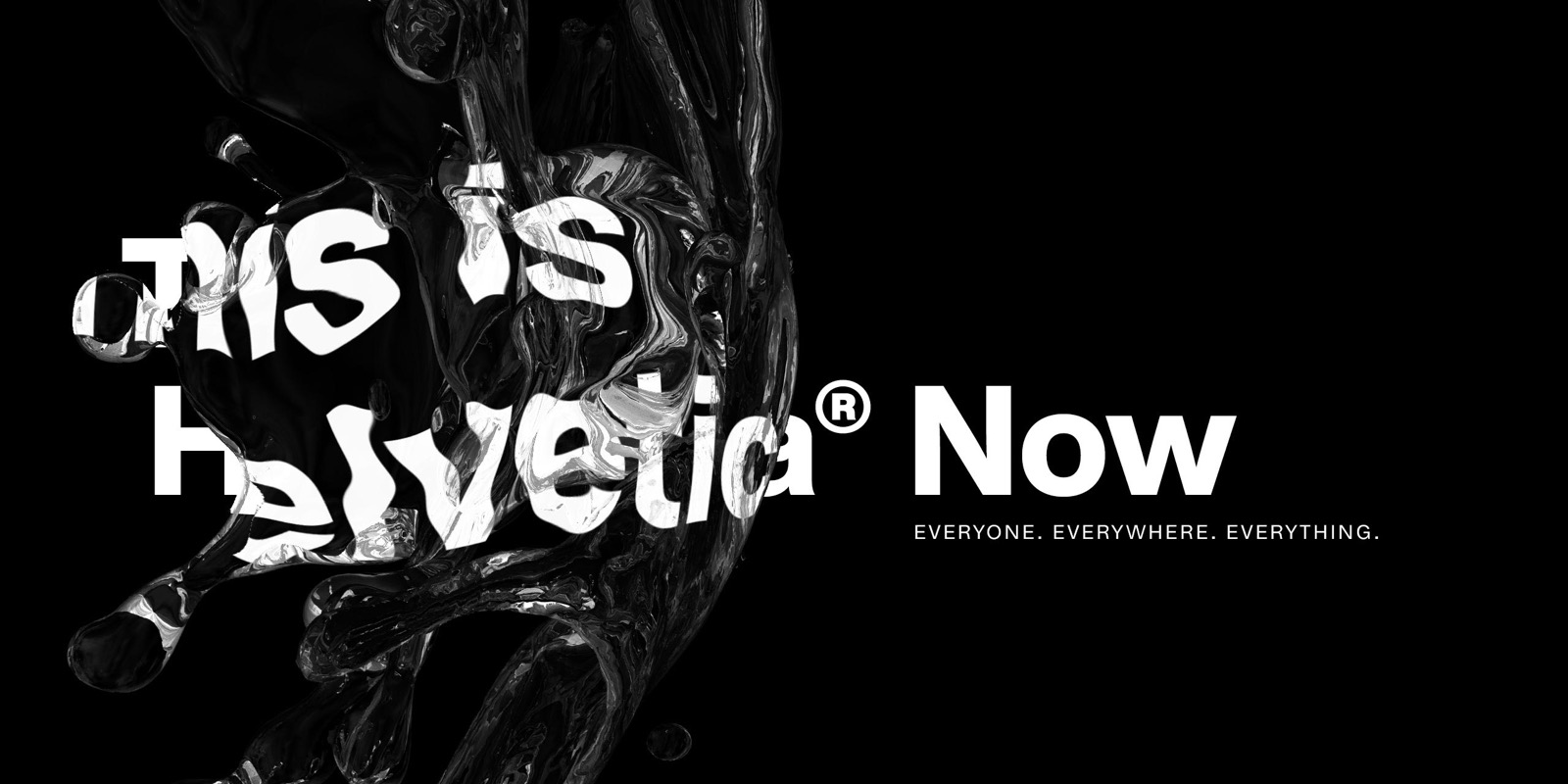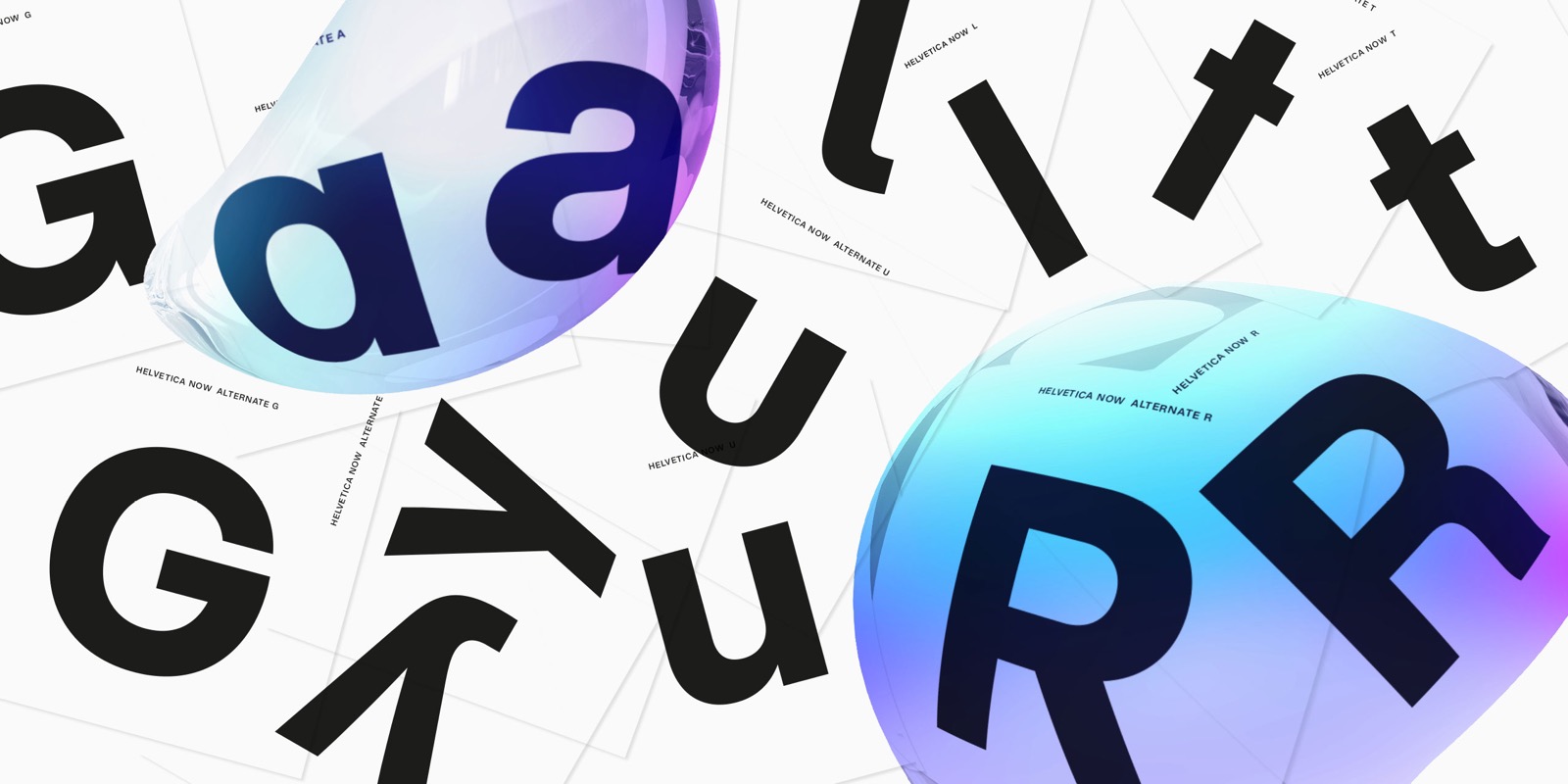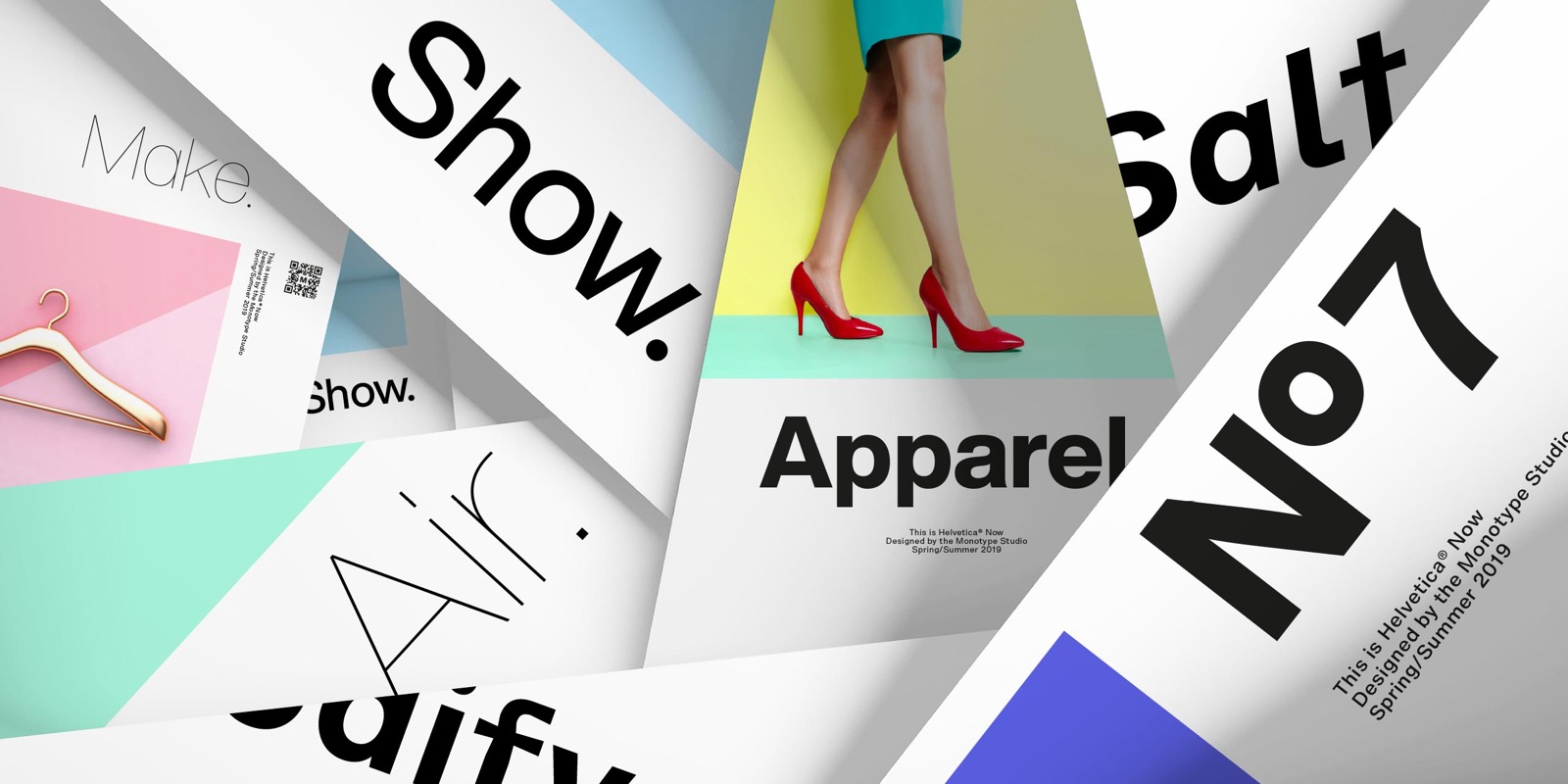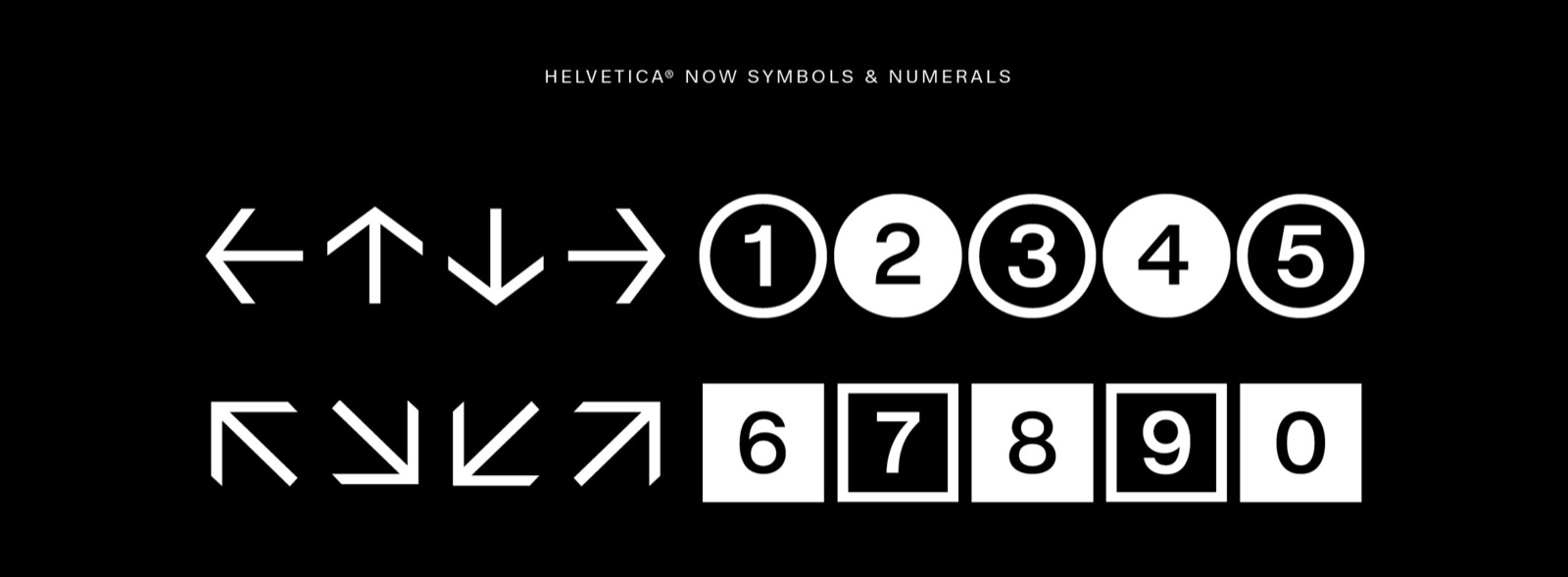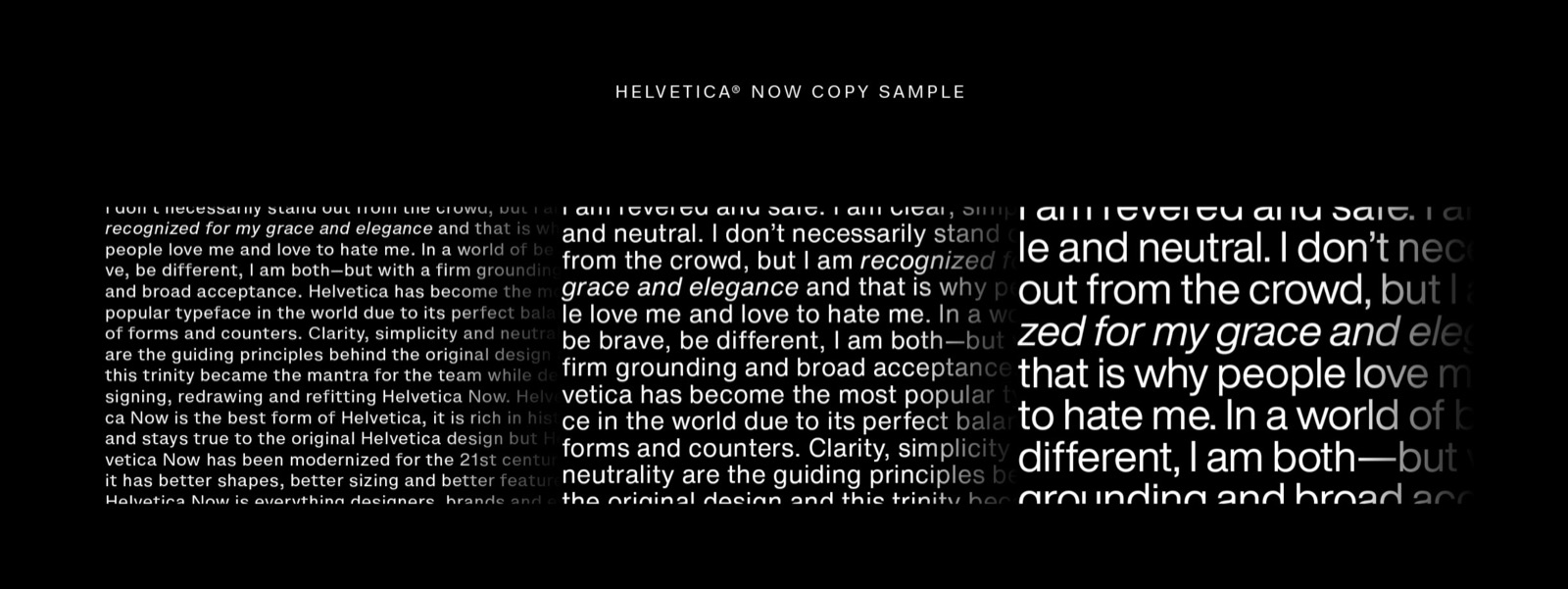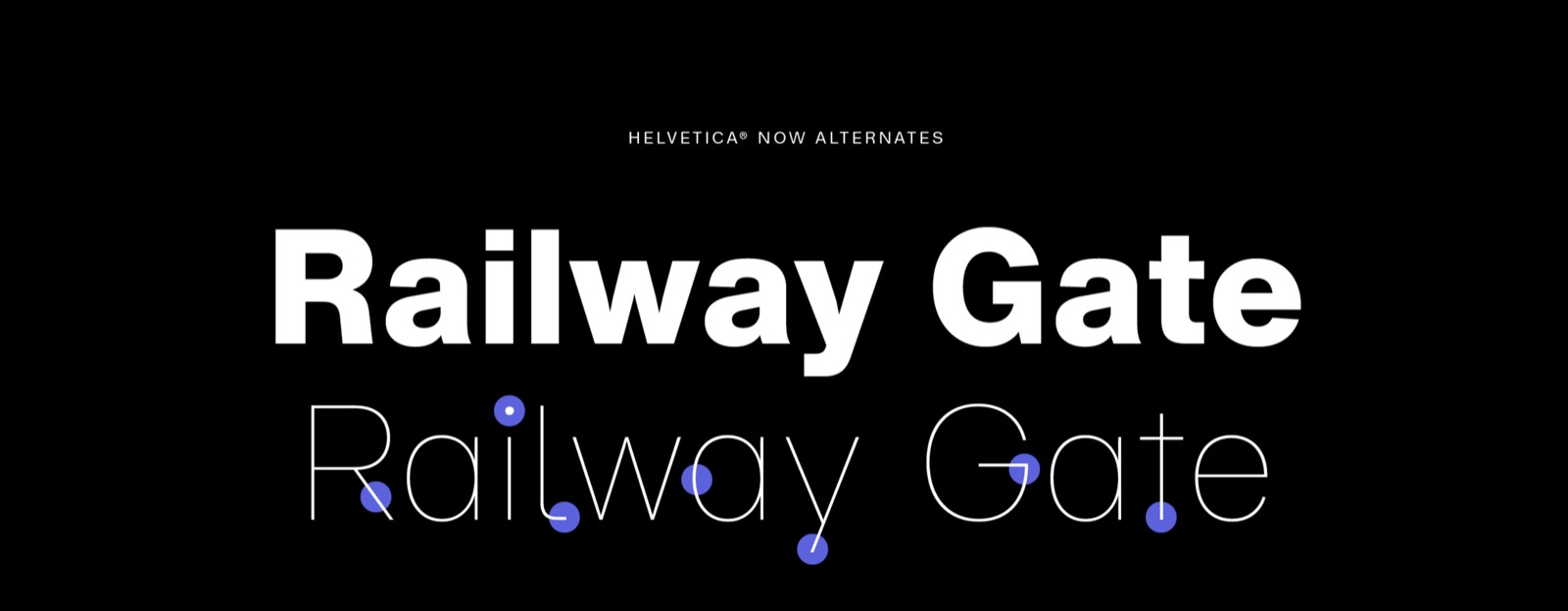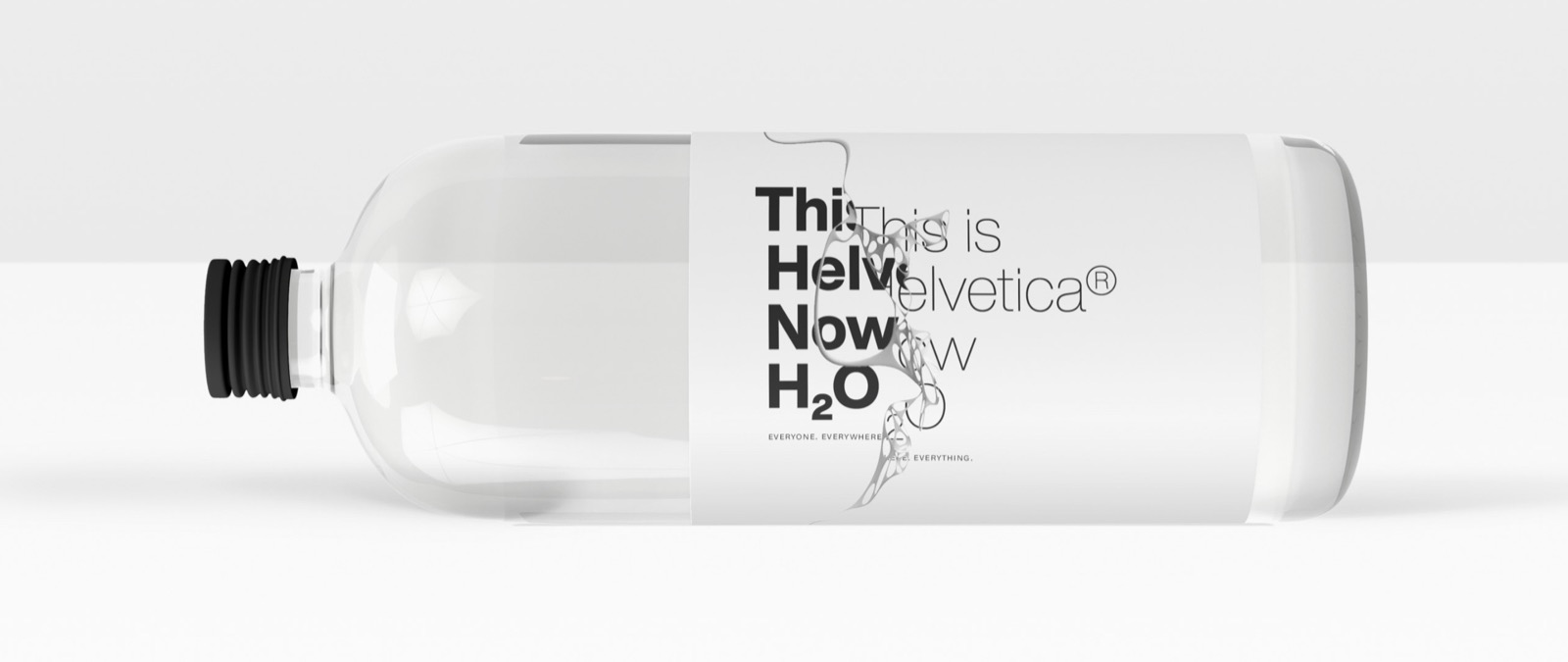
Intervista a Charles Nix: «Così abbiamo portato l’Helvetica nel 21° secolo»
Dell’Helvetica Now abbiamo già parlato, sia in occasione della sua presentazione ufficiale sia in un articolo di approfondimento sull’importanza che avrà a livello mediatico in tutto il mondo.
E siamo convinti che sia una cosa davvero interessante per diversi aspetti: molti dei nostri lettori sono grafici, designer, scrittori, illustratori e più o meno tutti, prima o poi, si sono chiesti come sia il lavoro di un disegnatore di font, che cosa lo porti ad una pratica che è sicuramente più complessa e affasciante di quanto sembri: gli aspetti che si nascondono dietro la scelta di un particolare design sono molto articolati, specie nel caso dell’Helvetica, il cui design è rimasto pressoché inalterato negli ultimi 35 anni.
Intervista a Charles Nix, uno dei creatori di Helvetica Now
Così abbiamo colto la palla al balzo quando ci si è prospettata l’occasione di parlare con Charles Nix, attualmente Type director in Monotype: nella sua carriera ha impresso la firma su un numero importante di caratteri come il Walbaum e l’Hope Sans, che hanno ricevuto il Certificate of Typographic Excellence nel ventiduesimo Annuario del Type Directors Club Typeface Design Competition e nella sua carriera trovano posto anche la creazione di font per Google e Progressive Insurance.
Iniziando progettando libri in una piccola casa editrice, Charles ha messo a frutto la sua esperienza in editoria, marketing e pubblicità per offrire nel suo design una prospettiva unica, che poi si è inevitabilmente riflessa anche sull’Helvetica Now.
Tra le attività di Charles, spicca anche quella di insegnante: oltre a presiedere alla cattedra in diversi istituti tra la Malesia e New York, ha offerto anche diversi training su LinkeIn Learning, anche sulla creazione di font.
Charles Nix, Type director in Monotype e uno dei creatori di Helvetica Now
Charles , da quanto ho capito, prima di lavorare in Monotype come designer, dirigevi un piccolo studio editoriale: è stato difficile per te cambiare da compositore grafico a disegnatore di font?
È vero, avevo un piccolo studio editoriale, e ho progettato libri per molto tempo, tanto quanto ho disegnato font. È stato difficile? Non particolarmente. È un piacere applicare quanto ho imparato come compositore nella fase di creazione dei caratteri. Amo il Team Studio di Monotype, è un gruppo con grande talento, affabile e collegiale, e profondamente dedicato alla creazione di grandi famiglie di font.
Come è nato Helvetica Now? Perché l’Helvetica e quali sono state le motivazioni che hanno spinto il progetto?
Quando il progetto è stato concepito per la prima volta, erano passati 35 anni dall’ultima grande riprogettazione dell’Helvetica. È un periodo molto lungo, soprattutto in una ottica digitale (e di font digitali). È stato costruito per un altra era, in un tempo molto meno dipendente dallo schermo (e con altre risoluzioni, ndr).
Quell’Helvetica, chiamato Helvetica Neue, è stato digitalizzato da un unico master di disegno che è stato ottimizzato per lavorare bene come testo. L’Helvetica pre-digitale aveva piccoli aggiustamenti, ma importanti per la resa a piccole, medie e grandi dimensioni. Volevamo che quel dettaglio specifico (quello che i tipografi chiamano “dimensione ottica” o “multiple masters”) ritornasse.
Una delle caratteristiche più importanti di Helvetica Now è la ricchezza di glifi alternativi
È stato anche molto importante quello che abbiamo imparato dai nostri clienti durante i 35 anni (e più) di utilizzo del font. Quello che chiedono davvero è la possibilità di avere glifi alternativi: abbiamo imparato che le caratteristiche e i glifi dei font che hanno utilizzato sono diventati insufficienti per l’utilizzo moderno, come ad esempio il carattere “@” oppure i simboli delle nuove valute (tra cui l’Euro, comparso nel nuovo millennio, più di quindici anni dopo l’Helvetica Neue, ndr). Infine, abbiamo capito che il loro inserimento migliora la vita di un grafico, come anche l’aggiunta di simboli come le frecce, numeri cerchiati e quadrati.
Le possibilità del progetto erano enormi. Abbiamo passato l’ultimo anno e mezzo a ridisegnare ogni glifo della famiglia, quasi 40.000 caratteri in tutte le dimensioni ottiche. Abbiamo anche adeguato la distanza tra i caratteri per garantire una maggiore leggibilità. É stata una impresa enorme.
Nella pagina dell’Helvetica Now di Monotype.com, è possibile leggere che la pianificazione del font è stata uno sforzo di squadra: come è stato lavorare in team per l’Helvetica Now? Ognuno aveva un singolo stile o glifo oppure era un lavoro di gruppo per ogni singolo dettaglio?
Come ho detto, la squadra di Monotype è fantastica e lavorare con loro è stato un vero piacere. È stato un lavoro duro e molto intenso, ma mi è piaciuto molto. Una squadra ha lavorato allo stile Displaye l’altra sugli stili Text and Micro. Successivamente, ad un’altra squadra è stato dato il lavoro per lo stile Italico. Tutti i disegni e le prove sono stati rivisti dalla squadra più grande. E una volta che un progetto finiva, un’altra squadra era pronta per la finalizzazione tecnica del font.